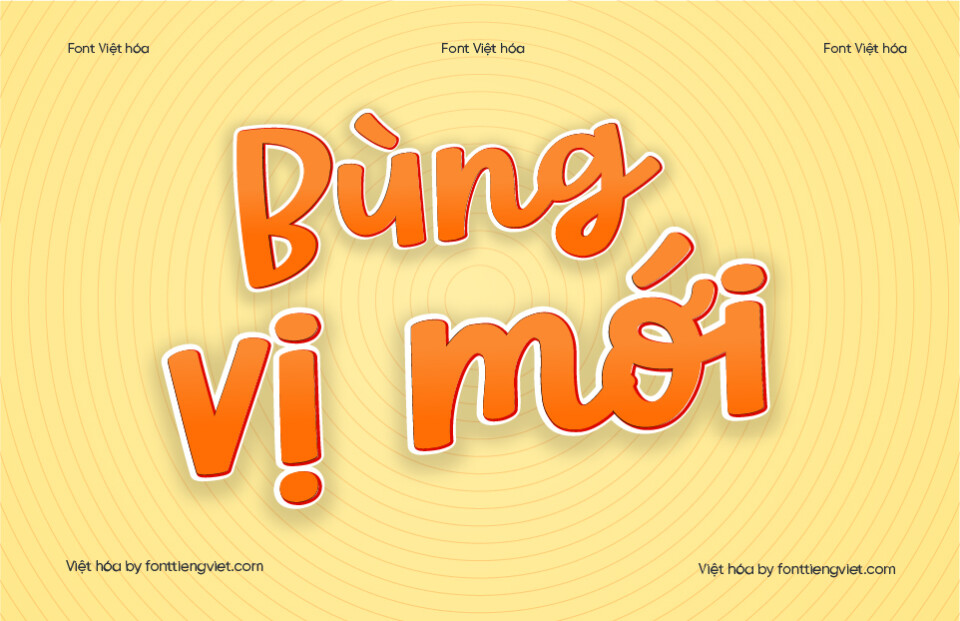
Font Việt hóa 1FTV VIP Hello Farmer – Font ẩm thực
Giới thiệu bộ Font Việt hóa 1FTV VIP Hello Farmer – Font ẩm thực
Trong thế giới đồ họa hiện đại, việc lựa chọn Font Miễn Phí phù hợp đóng vai trò then chốt tạo nên linh hồn cho tác phẩm. Bộ Font Việt hóa 1FTV VIP Hello Farmer – Font ẩm thực là một siêu phẩm thiết kế mang phong cách mộc mạc, gần gũi và đầy sức sống. Đây là giải pháp hoàn hảo cho những dự án yêu cầu tính thẩm mỹ cao, từ thực đơn nhà hàng đến bao bì nông sản Việt.
Đặc điểm nổi bật của Font Việt hóa 1FTV VIP Hello Farmer – Font ẩm thực
Bộ chữ này gây ấn tượng mạnh nhờ những đường nét mềm mại nhưng vẫn giữ được cấu trúc chắc chắn. Kiểu dáng của nó mô phỏng sự chân chất của những người nông dân, mang lại cảm giác ấm cúng và tin cậy. Các ký tự tiếng Việt được tinh chỉnh tỉ mỉ, giúp việc trình bày văn bản trở nên chuyên nghiệp, không bị lỗi dấu hay khoảng cách.
Ứng dụng Font Việt hóa 1FTV VIP Hello Farmer – Font ẩm thực trong thực tế
Nếu bạn đang tìm kiếm một phông chữ chuyên dụng cho ngành ăn uống, sản phẩm này chính là câu trả lời. Font Việt hóa 1FTV VIP Hello Farmer – Font ẩm thực cực kỳ phù hợp để làm tiêu đề trên các poster quảng cáo, hình ảnh mạng xã hội hoặc thiết kế logo cho các cửa hàng thực phẩm sạch. Ngoài ra, tính ứng dụng cao giúp nó dễ dàng kết hợp với các bộ chữ không chân khác để tạo sự cân bằng.
Lý do nên sử dụng Font Việt hóa 1FTV VIP Hello Farmer – Font ẩm thực